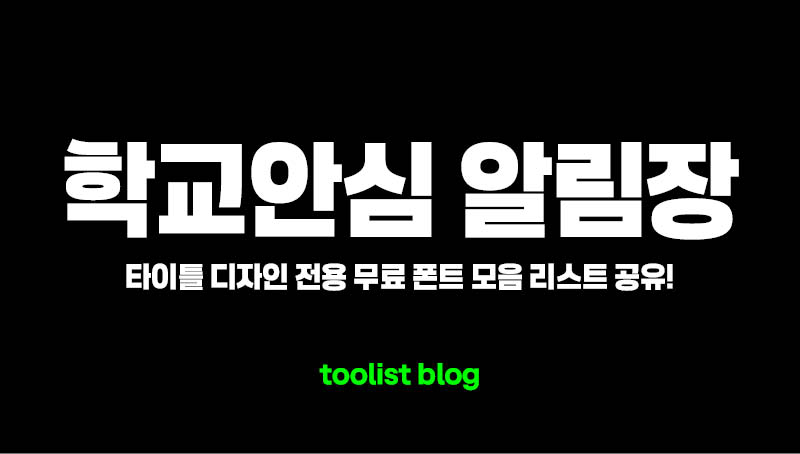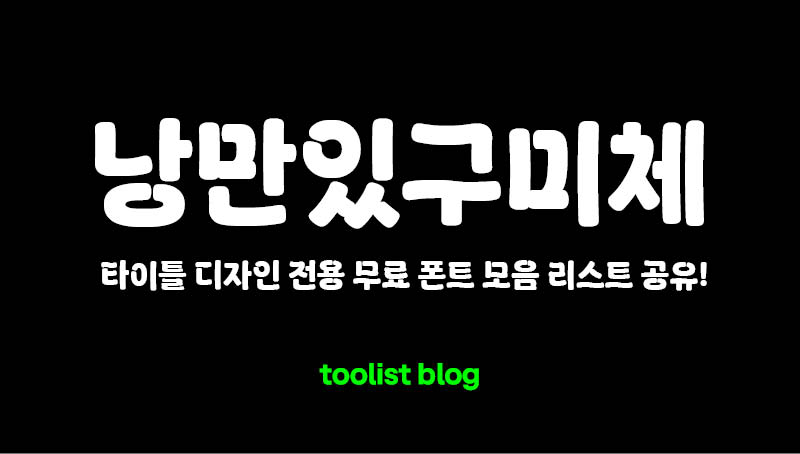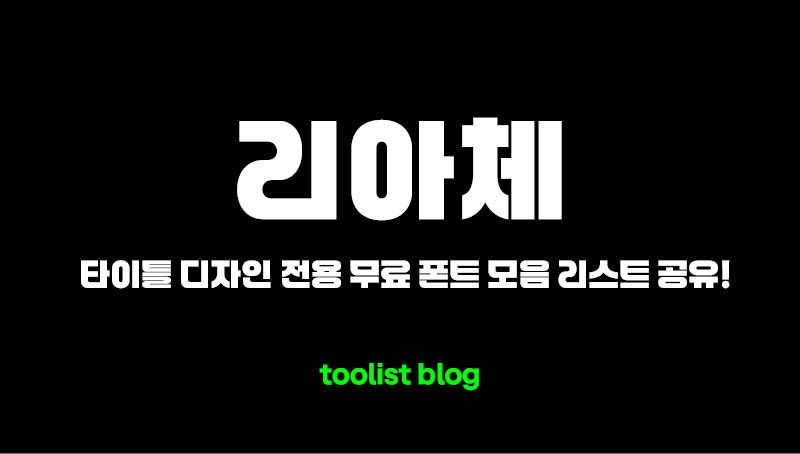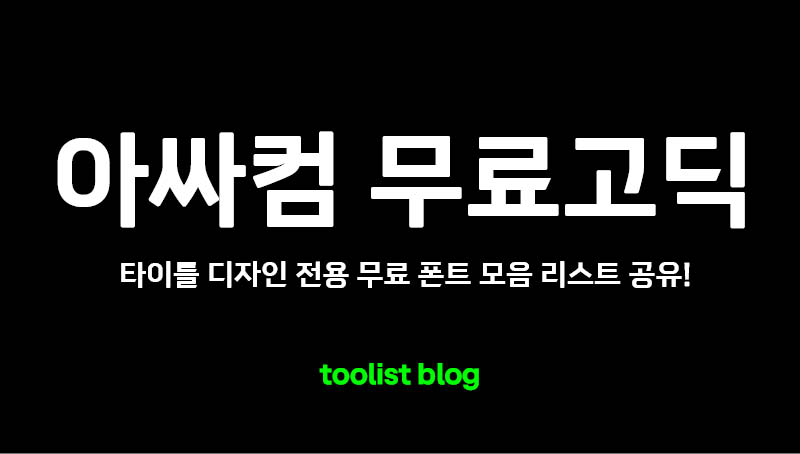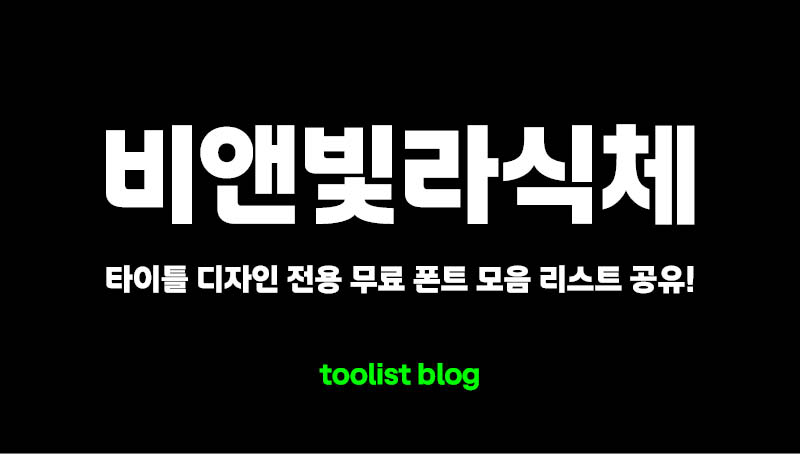
ppt나 디자인할때에 타이틀을 쓸 경우, 가시성이 좋고 포인트가 될 수 있으며 되도록이면 헤드라인이 굵은 서체를 사용한다. 예전부터 계속적으로 써오는 G마켓산스체나 여기어때체나 너무나 많지만 요즘엔 무료서체가 너무 다양하게 나오고, 디자이너는 계속 고민을 해야하기때문에 여러 서체들을 접해봄이 좋을 것 같아 공유하니 참고하길 바란다. 물론 회사 보고용이나 PPT등에도 활용할 수 있으니 참고하고, 자세한 폰트 라이선스 규정은 각 폰트마다 설명해두거나, 그 폰트를 만든곳에서 규정하는 규약들을 링크걸어둘테니 꼭 확인하고 사용하길 바란다.
비앤빛라식체
강남의 비앤빛안과에서 만든 자체 폰트로 아무래도 안과에서 만든 서체이니 시인성이 좋고 가독성도 좋다. 또한 디자인도 나쁘지 않게 나와서, 카드뉴스나 이리저리 활용할 곳이 많은 서체이다. 무료 서체이나, 제한하는 업종(같은 안과 관련 업종 전체 제한)이 따로 있으니 비앤빛 글꼴 라이선스 정책 링크로 들어가 확인 후 사용하는게 좋다.
리아체
롯데리아에서 만든 서체로, 여러 무료폰트가 있지만 가독성이 좋고 딱떨어지는 타이틀 디자인으로 쓰기에는 리아체가적합한 것 같다. 모든 글자의 크기가 일정하고, 흐트러짐이 없어 강조하기에는 틀림없이좋은 것 같다. 나머지 다른 서체들은 약간의 디자인변형이 있으므로, 타이틀 서체로는 리아체를 사용하길 추천한다.
낭만있구미체
구미시에서 만든 서체로, 색다른 컨셉의 디자인을 할때나 정형화된 딱딱한 폰트를 사용하기 좀 그럴때 사용하기가 아주 적절하다. 이벤트나 즐거운 축제 느낌일때에 활용하면 좋을듯한 타이틀 폰트이다. 낭만있구미체의 라이선스 규정내용은 눈누 사이트의 링크를 가져왔으니 참고하길 바란다.
아싸컴 무료고딕
아싸컴이라는 곳에서 제작한 폰트로, 딱 떨어지는폰트 스타일이 매력적인 무료 폰트이다. 이 폰트는 굵은 서체가 많이 굵지 않고, 세련되게 떨어지는 폰트로 IT계열의 디자인에서 활용될때 쓰이면 괜찮을것 같고, PPT 작업 시에헤드 타이틀 폰트로 써도 좋을 것 같은 폰트이다. 이 폰트는 누구나 자유롭게 수정하고 재배포할 수 있으며, 유료판매만 안하면 된다.
학교안심 알림장
한국교육학술정보원에서 만든 폰트로 유료판매만 금지되어있고 나머지는 전체 다 활용가능한 폰트이다. 이래저래 카드뉴스나 타이틀로도 쓰기가 좋다. 학교안심 폰트는 종류가 여러가지 있는데, 눈누사이트에서 더 찾아보고 사용하면 좋을 것 같다.